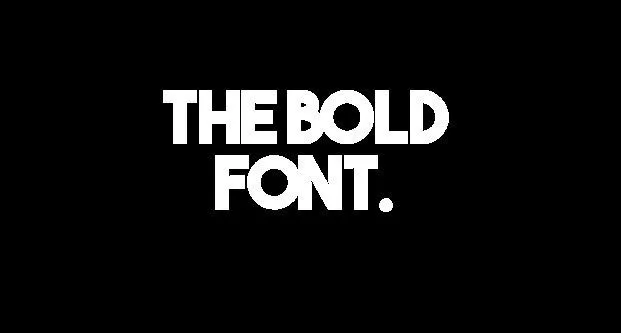
A The Bold Sans Font é uma escolha perfeita para designers que buscam uma fonte moderna e vibrante para seus projetos digitais. Com seu estilo sans serif, esta font combina elementos geométricos com influências humanistas, resultando em um design atraente e dinâmico. Foi projetada tanto para textos de destaque quanto para textos corpos, mantendo uma proporção equilibrada entre suas formas. A The Bold é ideal para qualquer tipo de projeto criativo que exija um toque moderno e forte, desde identidades digitais até materiais gráficos para o web ou impressão. Com seu design robusto e bem equilibrado, esta fonte se destaca como uma opção versátil e confiável em qualquer ambiente de criação visual.